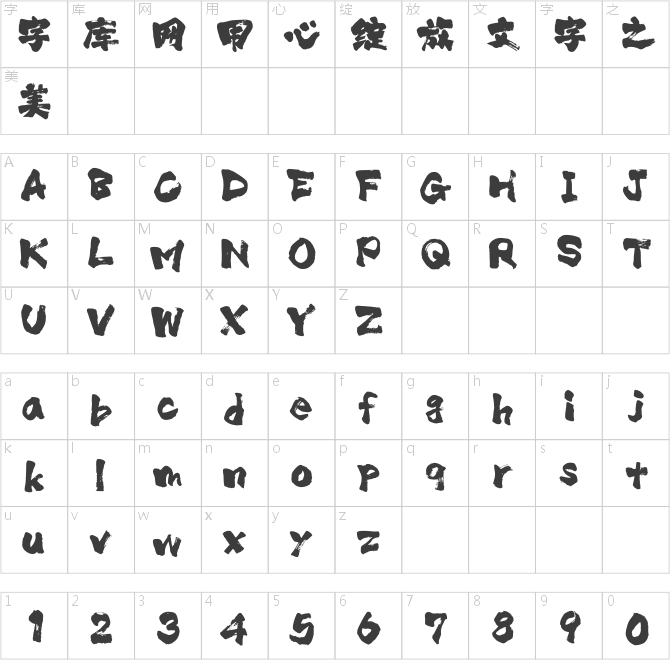
字体名称: 方正白舟武骨体
方正白舟武骨体
方正白舟武骨体的个性沉默、安静、天真、狂野、憨直、粗暴、倔强,代表男性的形象。这是一款中宫紧凑的方形字体,笔画粗壮有力,乍看之下像是一个不太成熟的未成年人,同时又呈现出一种稳健自若的精神面貌。运用枯笔书写出来的白舟武骨飞白鲜明、坚固厚实,给观者以一种倔强粗犷的印象,适用于大字招牌,和传统文化类的...